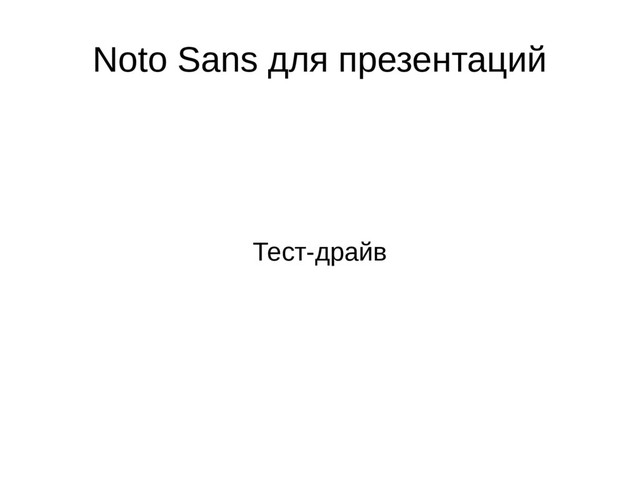
Продолжаем искать шрифт для презентаций
1. Arial Эпи́ стема (от греч. ἐπιστήμη «знание», «наука» и ἐπίσταμαι
«знать» или «познавать») — центральное понятие теории «археологии знания» Мишеля Фуко, введенное в работе «Слова и вещи. Археология гуманитарных наук» (1966).
2. Liberation Sans Эпи́стема (от греч. ἐπιστήμη «знание», «наука» и ἐπίσταμαι
«знать» или «познавать») — центральное понятие теории «археологии знания» Мишеля Фуко, введенное в работе «Слова и вещи. Археология гуманитарных наук» (1966).
3. Fira Эпи́стема (от греч. πιστήμη «знание», ἐ «наука» и πίσταμαι
«знать» или ἐ «познавать») — центральное понятие теории «археологии знания» Мишеля Фуко, введенное в работе «Слова и вещи. Археология гуманитарных наук» (1966).
4. Scada Эпи ́ стема (от греч. «знание», «наука» и «знать»
или «познавать») — ἐπίσταμαι центральное понятие теории «археологии знания» Мишеля Фуко, введенное в работе «Слова и вещи. Археология гуманитарных наук» (1966). • Греческий текст ломает выравнивание.